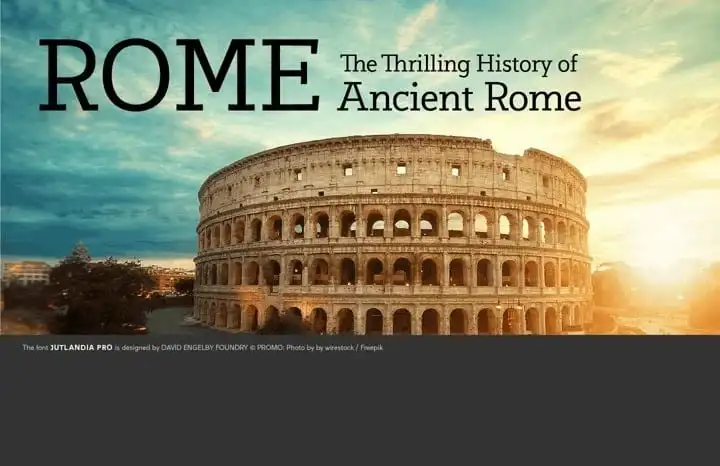
Jutlandia Pro Slab Serif Font – Download Grátis
Jutlandia Pro é uma linda fonte de tipo slab serif que combina elegância clássica com uma pitada moderna. Este design exclusivo foi criado pelo David Engelby Foundry e compartilhado para aqueles buscando um estilo sofisticado, capaz de criar impressões memoráveis. Seja para criar uma convidativa de casamento que ressalta o glamour de um dia especial ou para dar vida a um layout revolucionário em uma publicação semanal, Jutlandia Pro é uma escolha inteligente. Suas linhas finas e robustez suavizadas fornecem um toque vintage a qualquer design moderno. Além disso, ela pode ser usada como solução elegante para logo, slides de PowerPoint ou até mesmo como fonte de citações, oferecendo sempre um visual clean e retro. Jutlandia Pro é o tipo perfeito para aqueles que buscam uma transição suave entre a sofisticação clássica e a modernidade da interface digital.